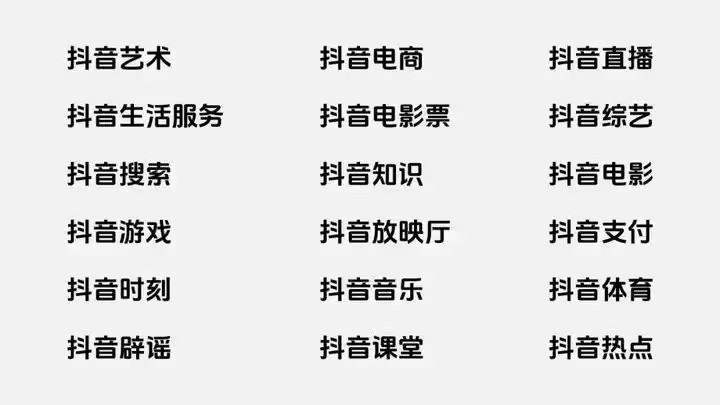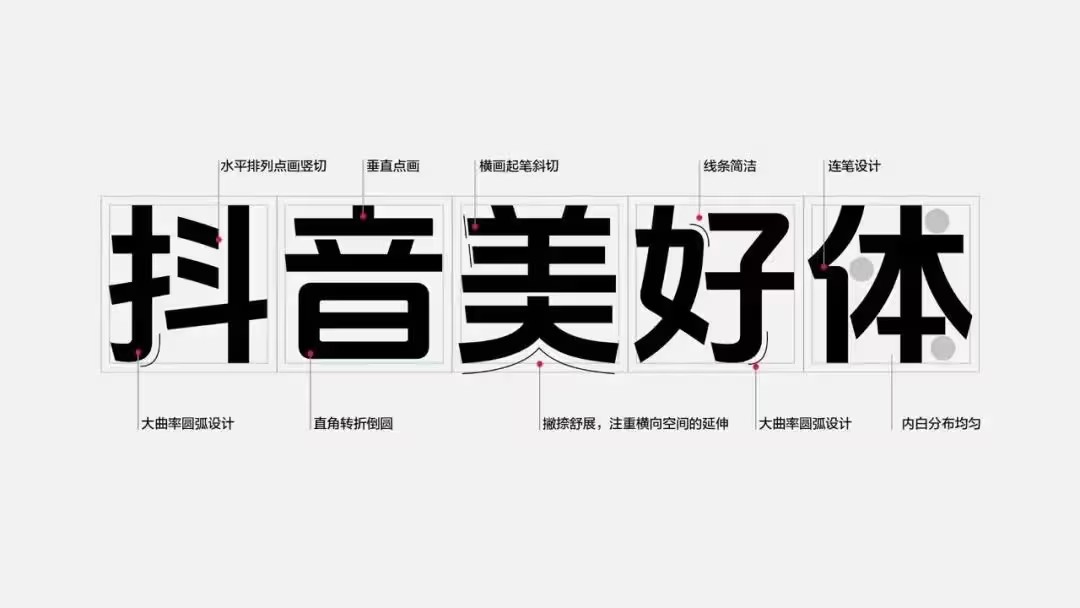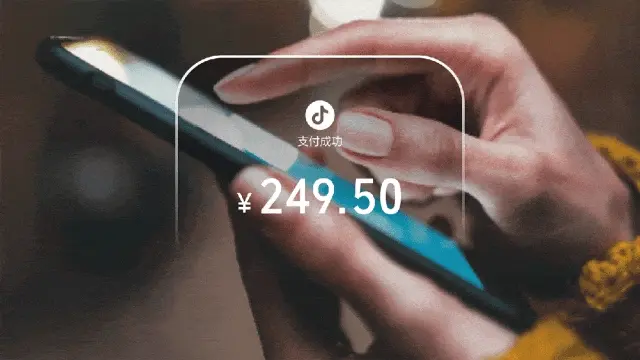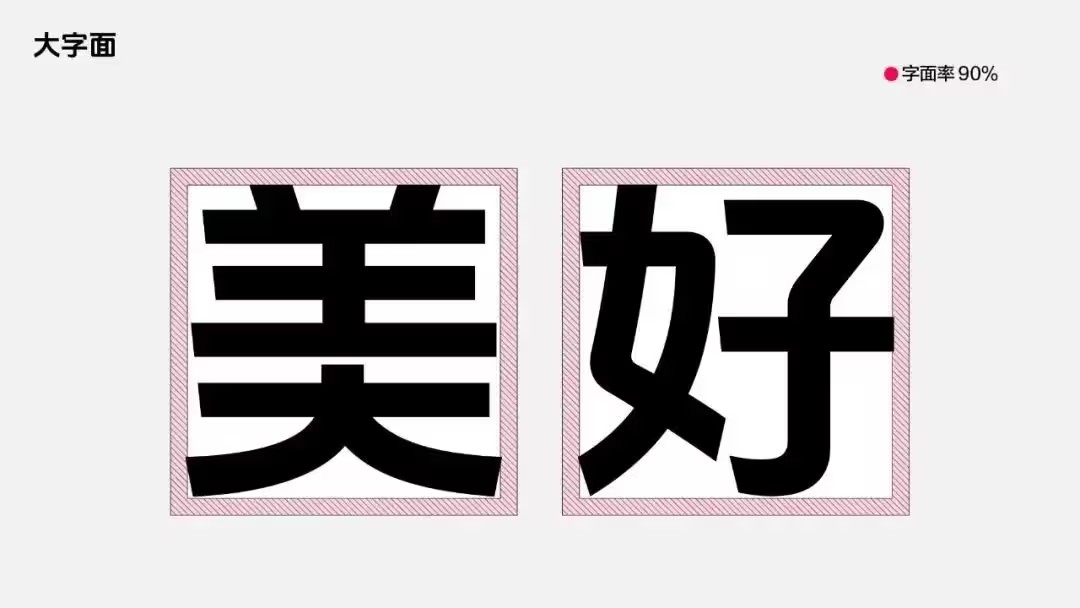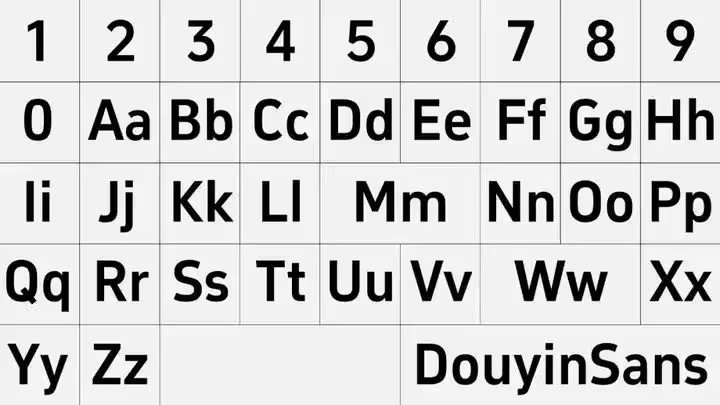
抖音美好体是一款品牌定制字体,由抖音集团在2023年联合专业字体团队方正字体共同设计,主要应用于数字屏幕阅读和短视频字幕场景。
“美好体”取自抖音“记录美好生活”的品牌理念,所在在设计上沿用了抖音logo的简约风格,Bold 字重的粗线笔画,内直外弧的圆角处理,即使是在分辨率低或者小字号场景下,也依然能保持清晰易读。
抖音美好体包含 6763 个中文字符和 682 个西文、数字符号。简体中文执行GB2312-80编码字符标准,西文采用几何风,两者相辅相成,中英文混排也能协调自然。